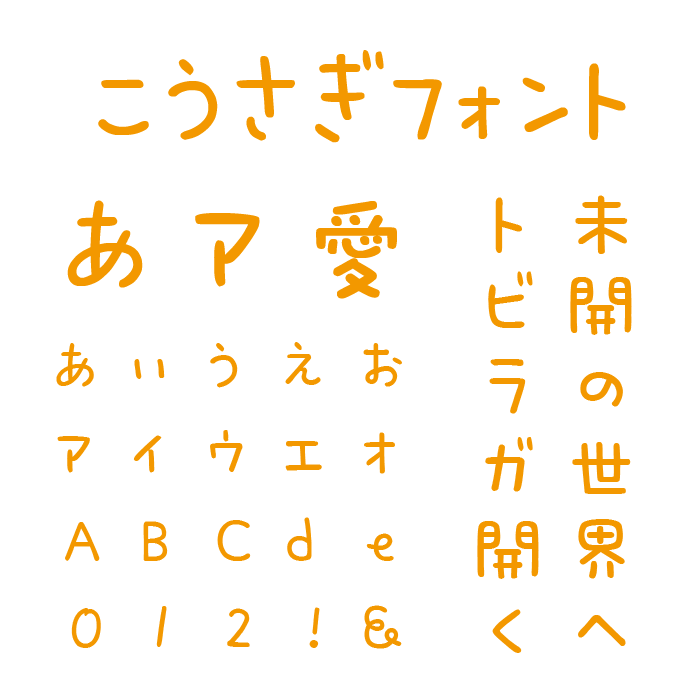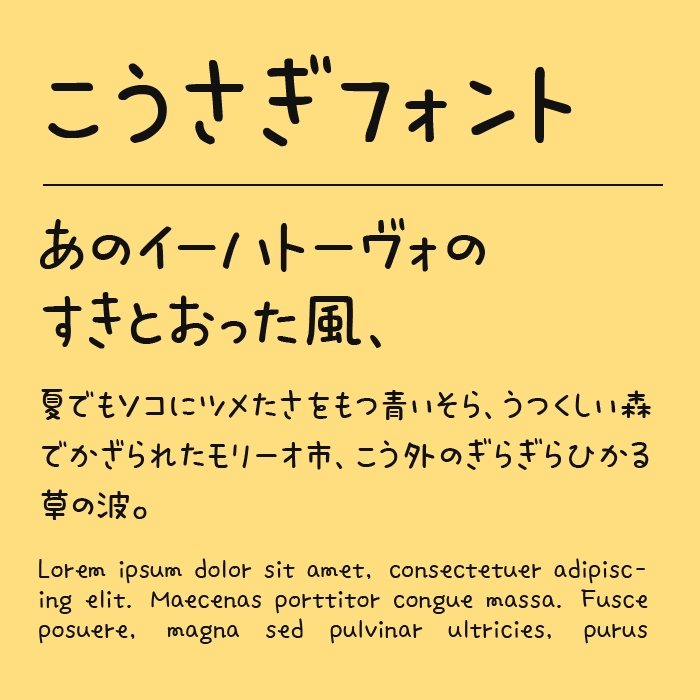
こうさぎフォントは、軽やかな跳ねるようなタッチが特徴の手書き風フォントです。
丸みのある線と、不揃いなリズムが、文字にぬくもりとあどけなさを感じさせます。線の端が丸く処理されており、絵本のようなやさしい世界観にもマッチします。
文字の太さや大きさが微妙に異なり、まるで子どもが丁寧に書いたような素朴さがあります。見る人の心をふっとほどくような、リラックス感のあるフォントです。保育・育児関連のタイトルや、やさしい気持ちを伝えたいシーンにぴったりなフォントです。